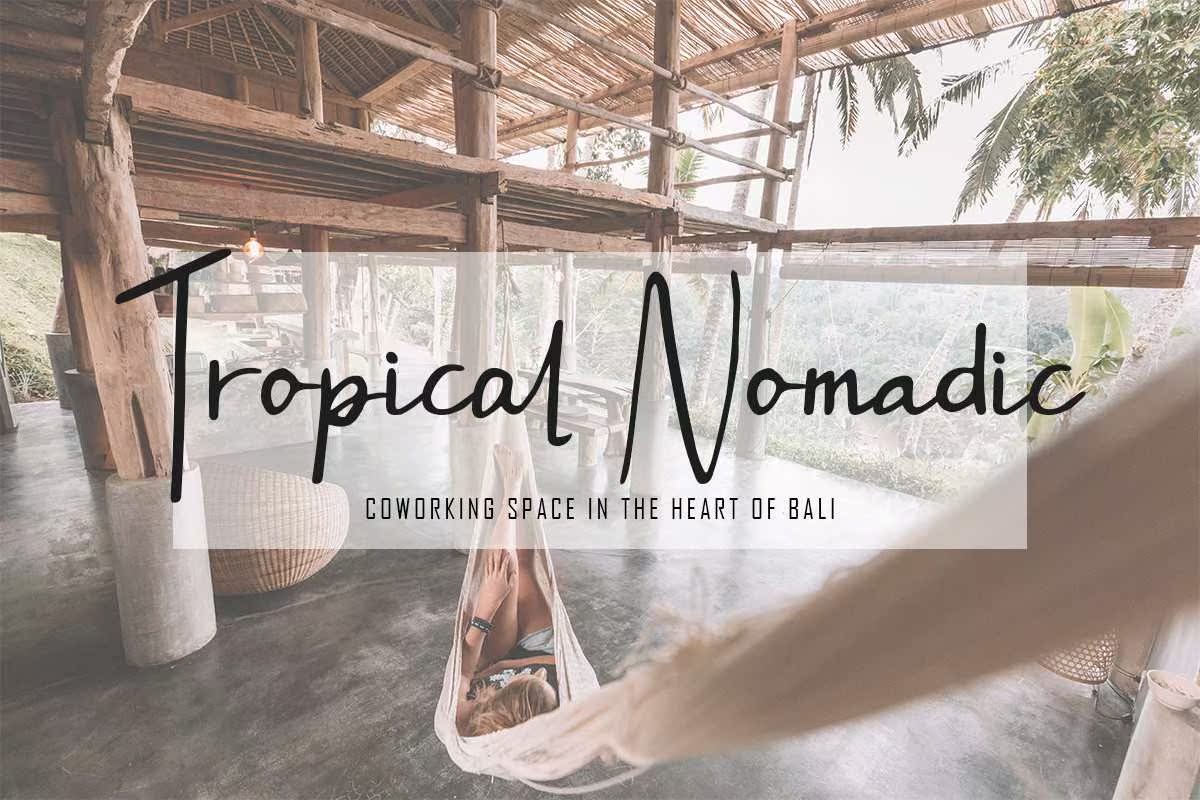
Jeannetténgetisamodernsignature Font让这款Fontlooks美观、简约、自然。这款Fontlooks适合任何需要精致优雅和手工品味的项目,如徽标和品牌、邀请函、文具、婚礼设计等。JeannetténgetisamodernsignatureFont让这款Fontlooks美观、简约,这款Font外观丰富,适合任何需要复杂优雅和手工品味的项目,如徽标和品牌、邀请函、文具、婚礼设计等